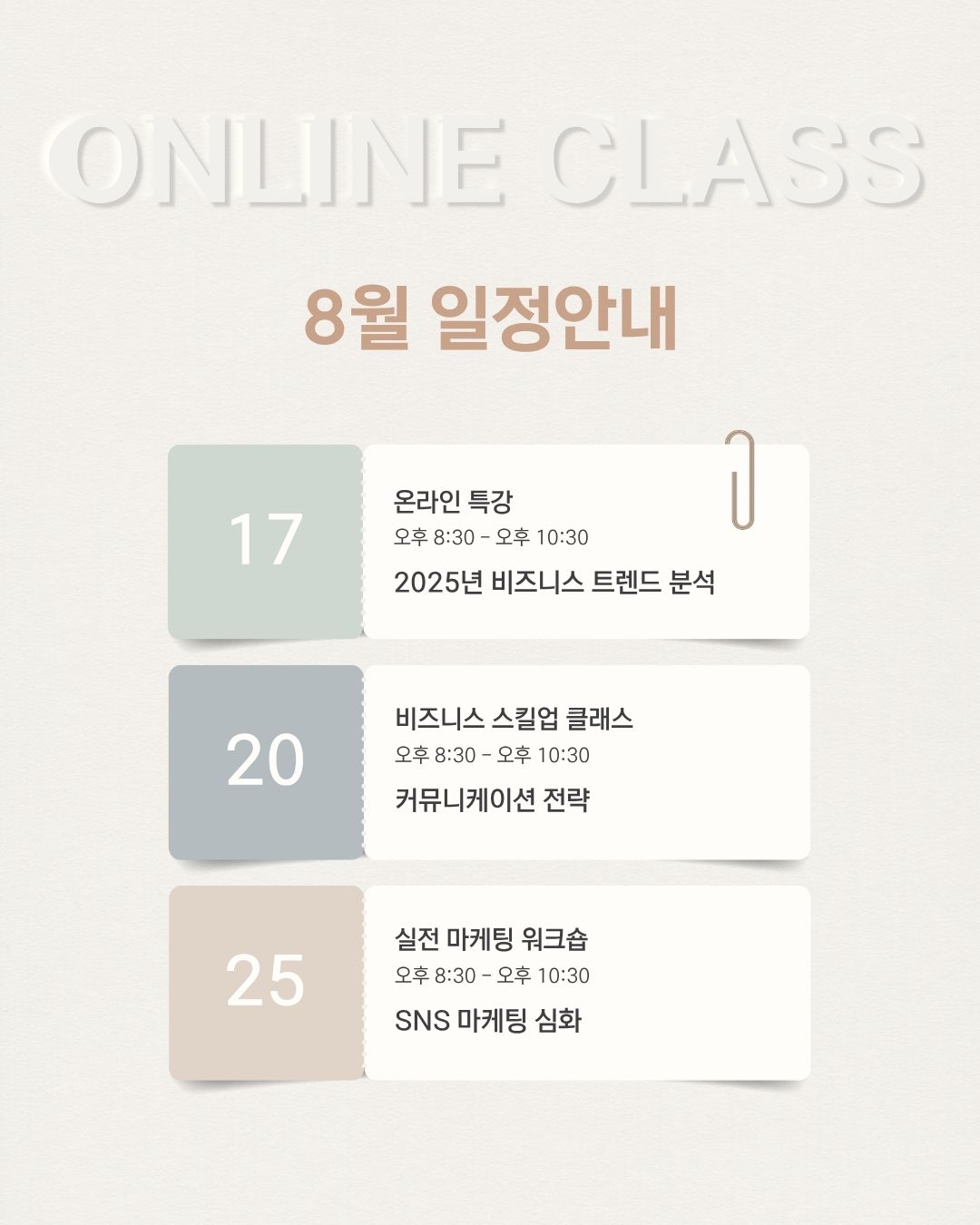
넥슨 Lv.2고딕 무료폰트
넥슨 Lv.2고딕 — 넥슨에서 배포하는 무료 폰트입니다. 좁은 글자폭과 단정한 자소 구성이 돋보이는 실용적이고 안정적인 고딕체
넥슨이 앞서 내놓은 Lv.1 고딕의 후속으로 만든 서체입니다. 이름의 레벨업이 그 관계를 그대로 말해 줍니다.
무엇을 바꿨는지가 분명합니다. 제작사 설명에 따르면 Lv.1 고딕을 기본 틀로 삼되 가독성은 높이면서 개성을 덜어내는 방향으로 개발했고, 글자의 장평을 좁혀 좁은 공간에 더 많은 글자를 넣으면서도 읽기 좋게 만들었습니다. 젊고 귀여운 Lv.1 고딕보다 성숙하고 어른스러운 느낌으로 완성됐다고 밝히고 있습니다.
그래서 넥슨의 서체 가운데 드물게 본문과 UI에 쓸 수 있는 실용적인 고딕입니다. 장평이 좁아 표나 캡션, 모바일 화면처럼 자리가 빠듯한 곳에 특히 유리합니다. 반대로 개성을 덜어낸 만큼 눈길을 끌어야 하는 제목에는 밋밋할 수 있습니다. 무료로 상업적으로 쓸 수 있지만 수정과 편집은 금지됩니다.